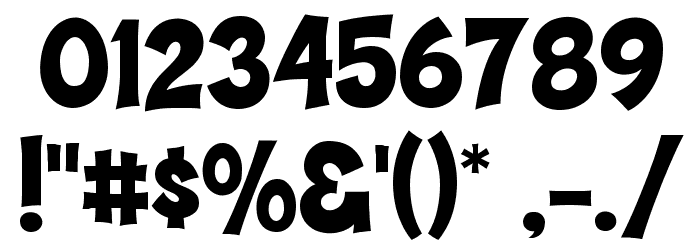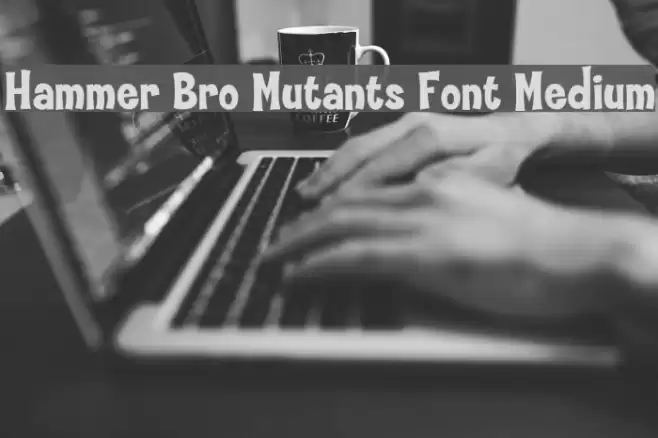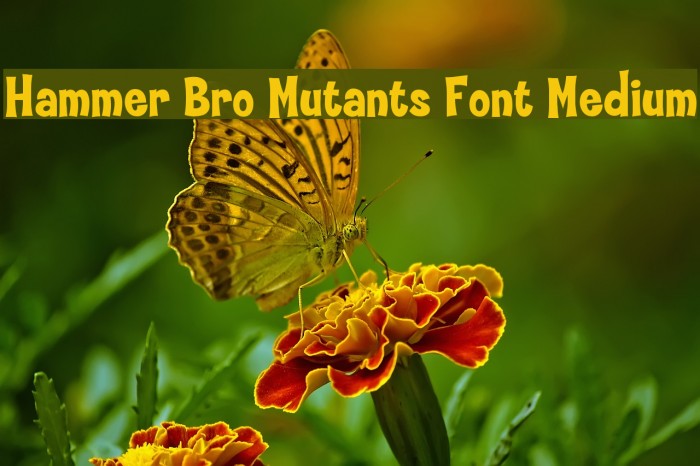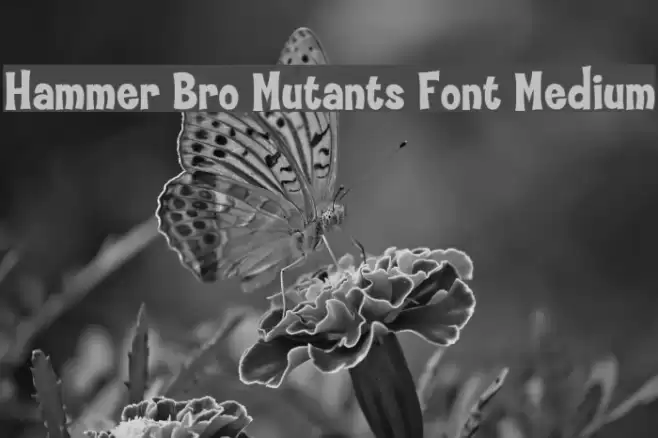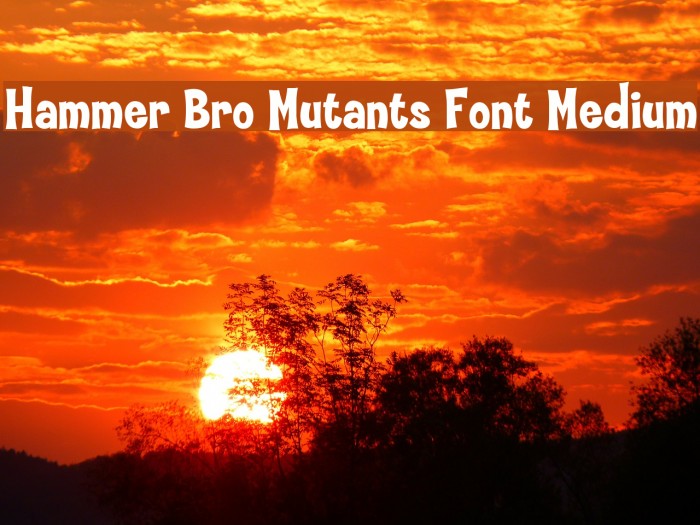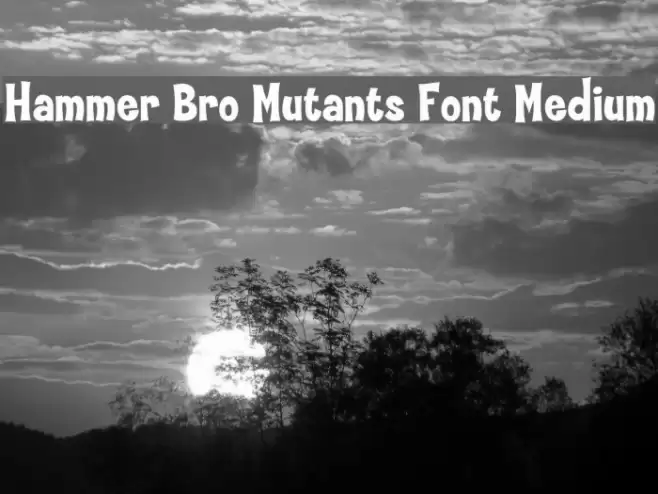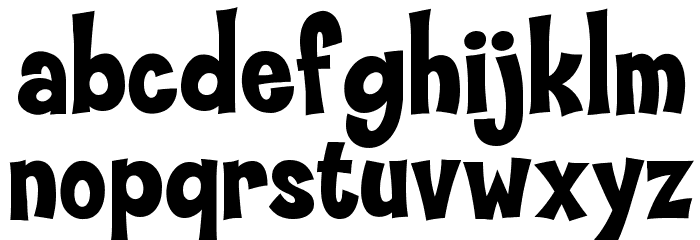
Hammer Bro Mutants Font Medium Font
| 全体的なスタイル | Playful, Whimsical, Bold |
| 用途 | Headlines, Posters, Branding |
| おすすめプロジェクト | Ideal for children's books, comic strips, playful branding, and eye-catching posters. |